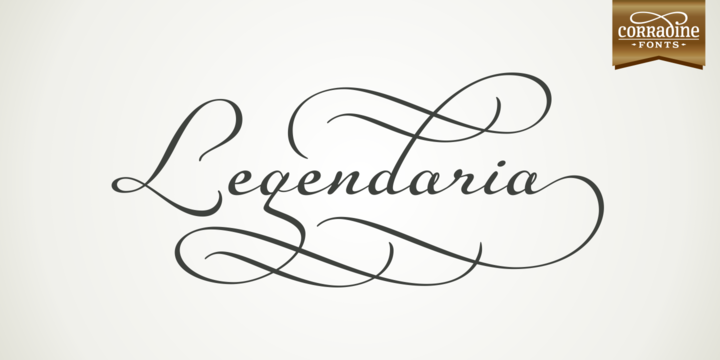
Legendaria é uma fonte de escrita cuneiforme extremamente sofisticada e elegante, conhecida por sua conectividade perfeita entre as letras. Com mais de 1300 caracteres decorados, esta fonte oferece incrível versatilidade para um grande número de aplicações, desde design gráfico até criação editorial digital. Entre os detalhes menos visíveis, notamos que a maioria das letras minúsculas dispõem de pelo menos 15 opções diferentes, incluindo caudas e ondas florais que proporcionam uma variedade visual impressionante. Esta fonte é perfeita para aqueles buscando um toque artístico em suas criações, seja você designer gráfico ou editor digital, Hamilton criou uma ferramenta única que vai tornar sua experiência de trabalho mais fluida e inspiradora.